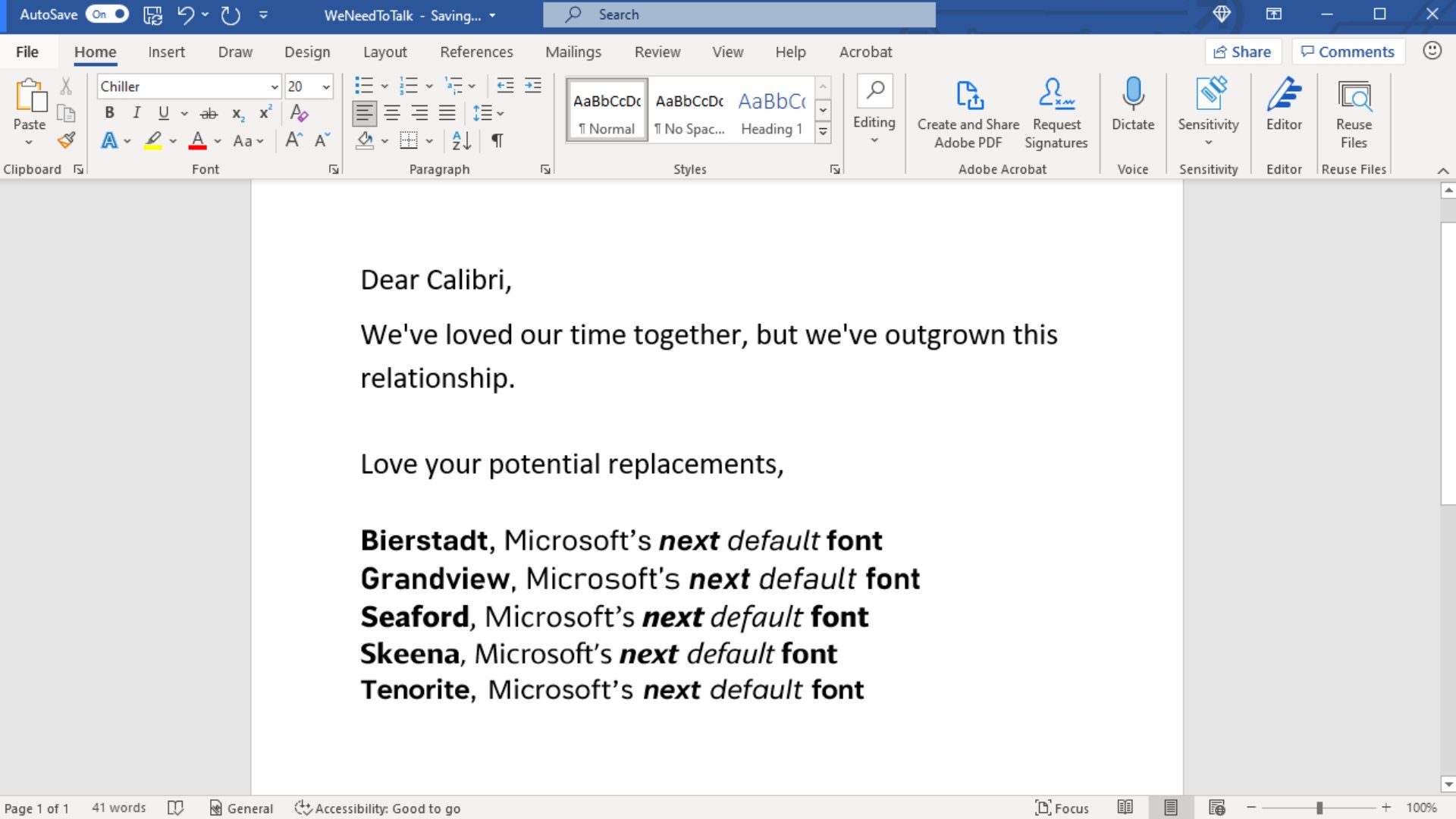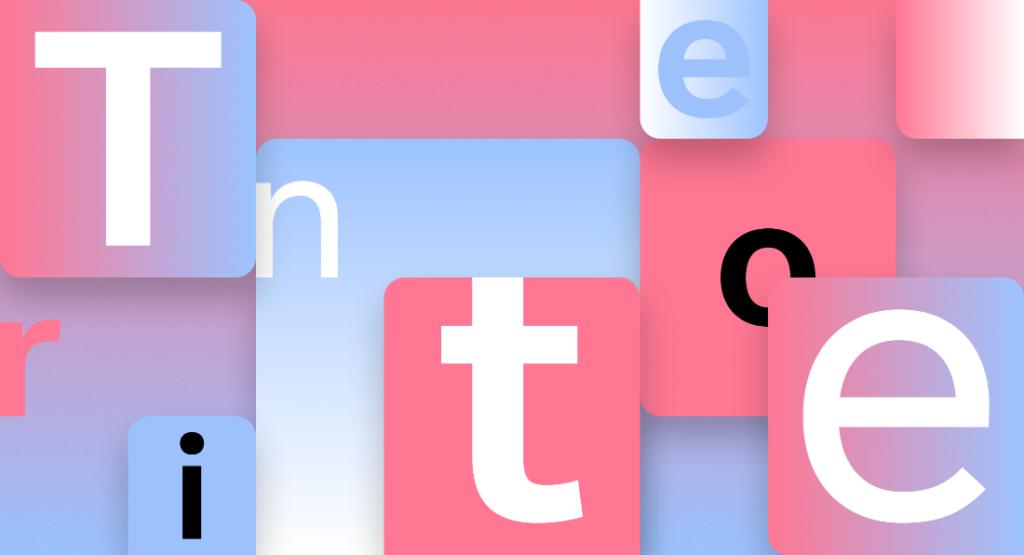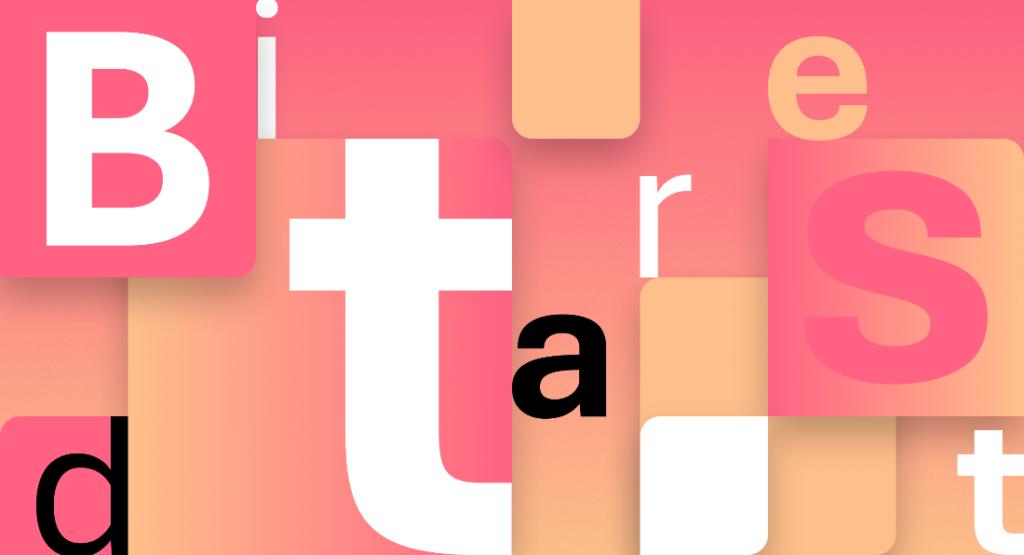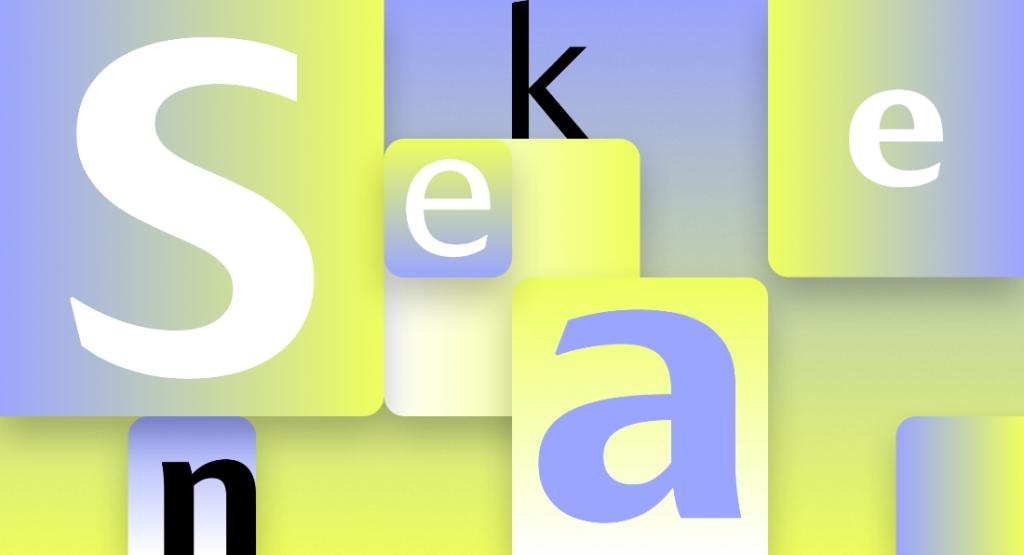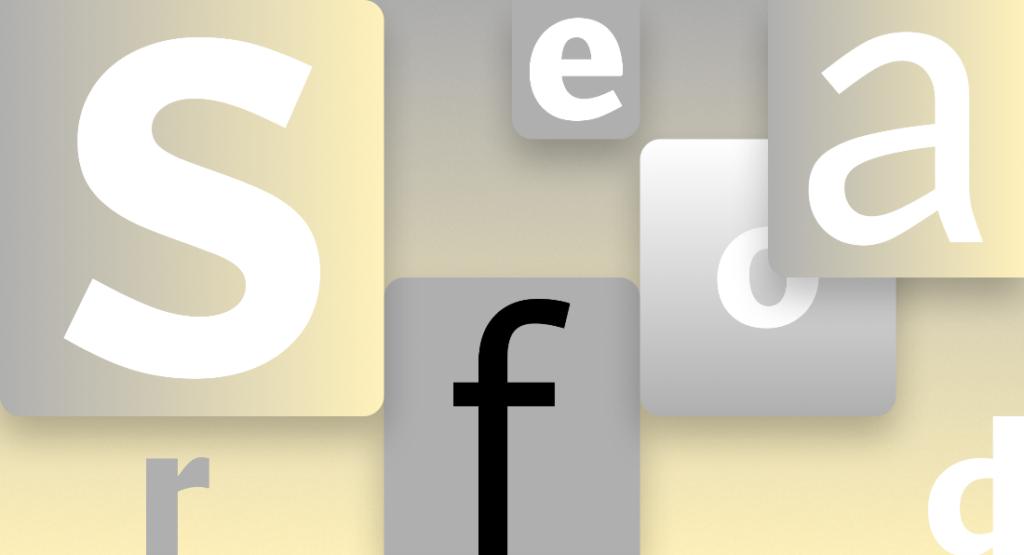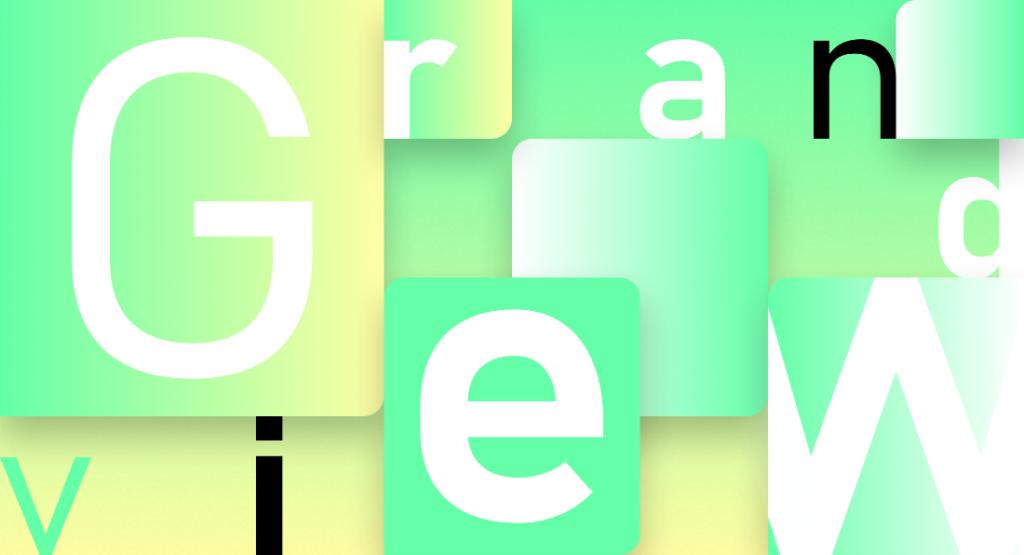
Microsoft löst Standard-Schriftart Calibri ab
Seit 2007 ist Calibri die Standardschriftart in Microsofts Office-Suite. Nun soll der Font einer neuen Schriftart Platz machen, wobei Microsoft fünf Kandidaten präsentiert und die Meinung der User erfragt.
Seit 2007 ist Calibri die Standard-Schriftart von Microsoft Office. Damals löste der Font Times New Roman ab. Nun ist es erneut Zeit für eine Umstellung, wie Microsoft via Blog ankündigt, wobei die Anwender ein Wörtchen mitreden sollen.
Microsoft stellt dazu fünf neu entwickelte Schriften vor, die der Konzern entwickeln liess und die die Namen Tenorite, Bierstadt, Skeena, Seaford und Grandview tragen. Alle kommen ohne Serifen aus und werden im Blog-Beitrag im Detail vorgestellt. Gleichzeitig ruft Microsoft die Userbasis auf, ihre Meinung dazu auf sozialen Medien zu teilen. Dieses Feedback wollte man dann sichten und sich danach für eine neue Default-Schrift entscheiden. Wie Microsoft zudem schreibt, solle niemand enttäuscht sein, wenn sein Favorit nicht zum Standard wird – alle fünf neuen Schriften sollen der Font-Auswahl von Office zugefügt werden.